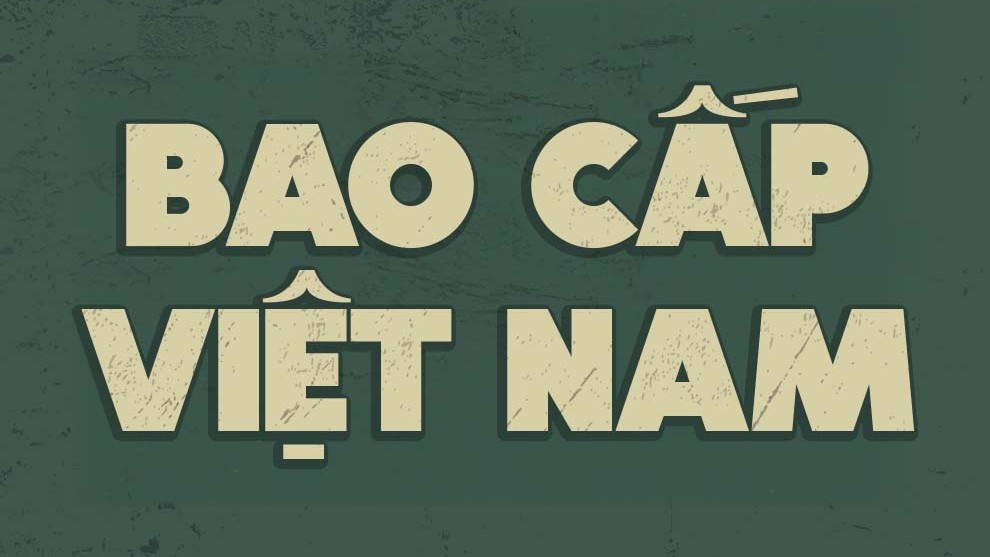
Phông chữ thời bao cấp gợi nhắc về một giai đoạn lịch sử đặc biệt của Việt Nam, nơi những tấm biển hiệu vẽ tay tỉ mỉ bằng bút lông và màu dầu đã trở thành biểu tượng văn hóa. Việc tải font chữ thời bao cấp giúp các kiến trúc sư, nhà thiết kế tái hiện không gian xưa cũ, mang lại chiều sâu cảm xúc và sự gần gũi cho các dự án homestay, quán cafe hay các ấn phẩm truyền thông di sản.
Đặc điểm thẩm mỹ của dòng phông chữ thời bao cấp Việt hóa
Khác với các kiểu chữ in ấn hiện đại, dòng font này mô phỏng sự ngẫu hứng của nghệ thuật vẽ biển hiệu đường phố, tạo nên một dòng chảy văn bản sinh động và giàu cá tính. Phiên bản font chữ thời bao cấp Việt hóa được tinh chỉnh kỹ lưỡng hệ thống dấu thanh, đảm bảo các ký tự đặc biệt như “ă, ê, ơ” hay các dấu hỏi, ngã không bị tách rời hay lệch tông so với cấu trúc hình khối của bộ gốc.
Sự ổn định về mặt thị giác của font thời bao cấp còn giúp người xem cảm nhận được tinh thần bền bỉ và tính thủ công. Trong kiến trúc, việc ứng dụng các bộ phông này tạo ra sự cân bằng thú vị khi phối hợp cùng các vật liệu hiện đại như panel, thép hộp hay kính cường lực. Đây là phương án hiệu quả để truyền tải thông điệp về lòng tự hào văn hóa và tư duy thẩm mỹ nhân văn, giúp công trình của bạn thoát khỏi những khuôn mẫu công nghiệp nhàm chán.
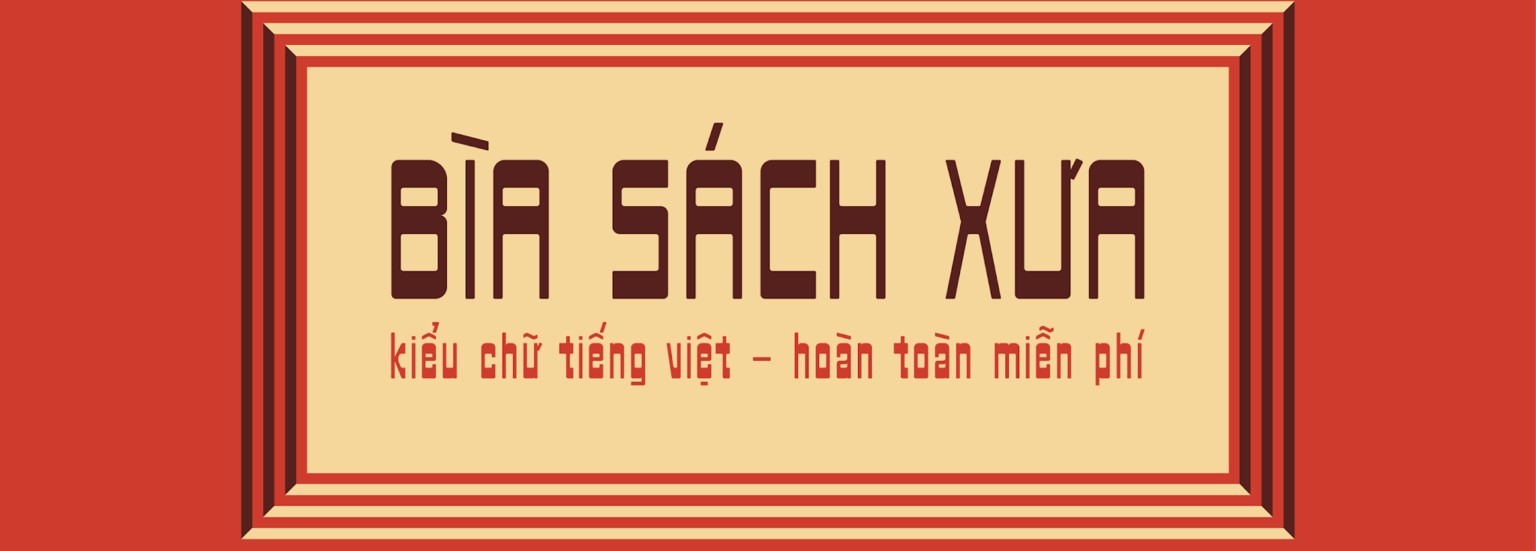
| Phân loại phong cách | Retro / Vintage / Sign Painting Vietnam |
| Nhóm phông tiêu biểu | Hòn Ngọc Viễn Đông, Gia Định, Classique Saigon |
| Mục đích phù hợp | Bảng hiệu hoài cổ, Poster, Decor nhà lắp ghép |
Tư vấn trình bày: Phông chữ phong cách bao cấp thường chiếm diện tích lớn do nét dày. Để bản thiết kế hài hòa, bạn nên phối hợp font chữ thời bao cấp việt hóa free cho các cụm từ nhấn mạnh và sử dụng phông không chân đơn giản cho phần thuyết minh chi tiết, giúp tổng thể bố cục trông chuyên nghiệp và thoáng đạt hơn.
03 Ứng dụng font chữ thời bao cấp vào thực tế kiến trúc
Nhờ diện mạo giàu tính gợi hình và dấu ấn thời gian rõ nét, bộ phông chữ này mang lại giá trị cao trong khâu trang trí và quảng bá các công trình kiến trúc:
- Hệ thống nhận diện cho Homestay & Khu nghỉ dưỡng hoài cổ: Những nét chữ từ việc tải font chữ thời bao cấp rất ăn ý khi xuất hiện trên biển hiệu gỗ, đá hoặc alu phủ màu trầm. Font chữ này giúp không gian toát lên vẻ ấm cúng, thu hút du khách yêu thích trải nghiệm văn hóa truyền thống.
- Trang trí không gian nội thất văn phòng: Bạn có thể dùng font này để vẽ tranh tường hoặc làm bảng slogan tại sảnh chờ văn phòng container, tạo điểm nhấn đầy thẩm mỹ và khơi gợi cảm hứng làm việc năng động cho nhân viên.
- Thiết kế bộ quà tặng doanh nghiệp: Sử dụng phông chữ thời kỳ cũ trên các nhãn dán sản phẩm hoặc thiệp cảm ơn giúp thương hiệu tạo được ấn tượng về sự tỉ mỉ, trân trọng các giá trị cốt lõi đối với khách hàng.
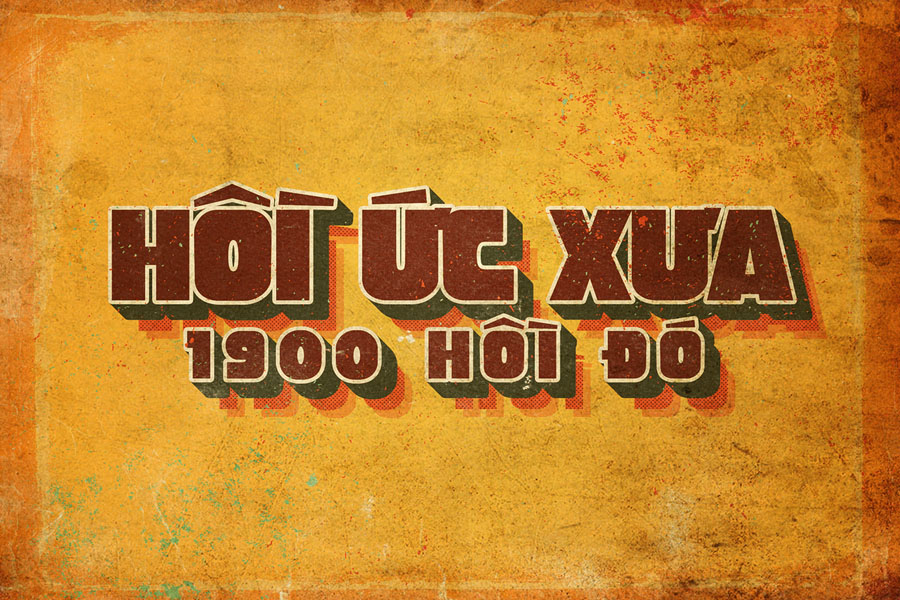
03 Lưu ý để bố cục phông chữ thời bao cấp chuyên nghiệp và tinh tế
Để khai thác hiệu quả vẻ đẹp của dòng font đặc thù này mà không làm rối mắt người xem, người thiết kế nên lưu tâm một số lưu ý kỹ thuật sau:
- Lựa chọn bảng màu đặc trưng: Phong cách bao cấp phát huy hiệu quả thị giác cao khi phối cùng các tông màu như vàng nghệ, cam cháy, xanh rêu đậm hoặc đỏ bordeaux. Tránh các màu neon quá hiện đại làm giảm đi sự trang trọng và chiều sâu văn hóa của bộ chữ.
- Kiểm soát khoảng cách dòng: Do cấu trúc chữ thường có các nét vươn rộng, bạn nên thiết lập khoảng cách dòng thoáng một chút để các dấu thanh tiếng Việt không bị chồng lấn, giữ được sự minh bạch cho văn bản khi nhìn từ xa.
- Sử dụng làm điểm nhấn duy nhất: Chỉ nên sử dụng font chữ thời bao cấp cho tiêu đề chính hoặc các câu slogan quan trọng. Việc lạm dụng cho toàn bộ nội dung thuyết minh kỹ thuật sẽ gây mỏi mắt và làm mất đi trọng tâm thẩm mỹ của bản thiết kế.